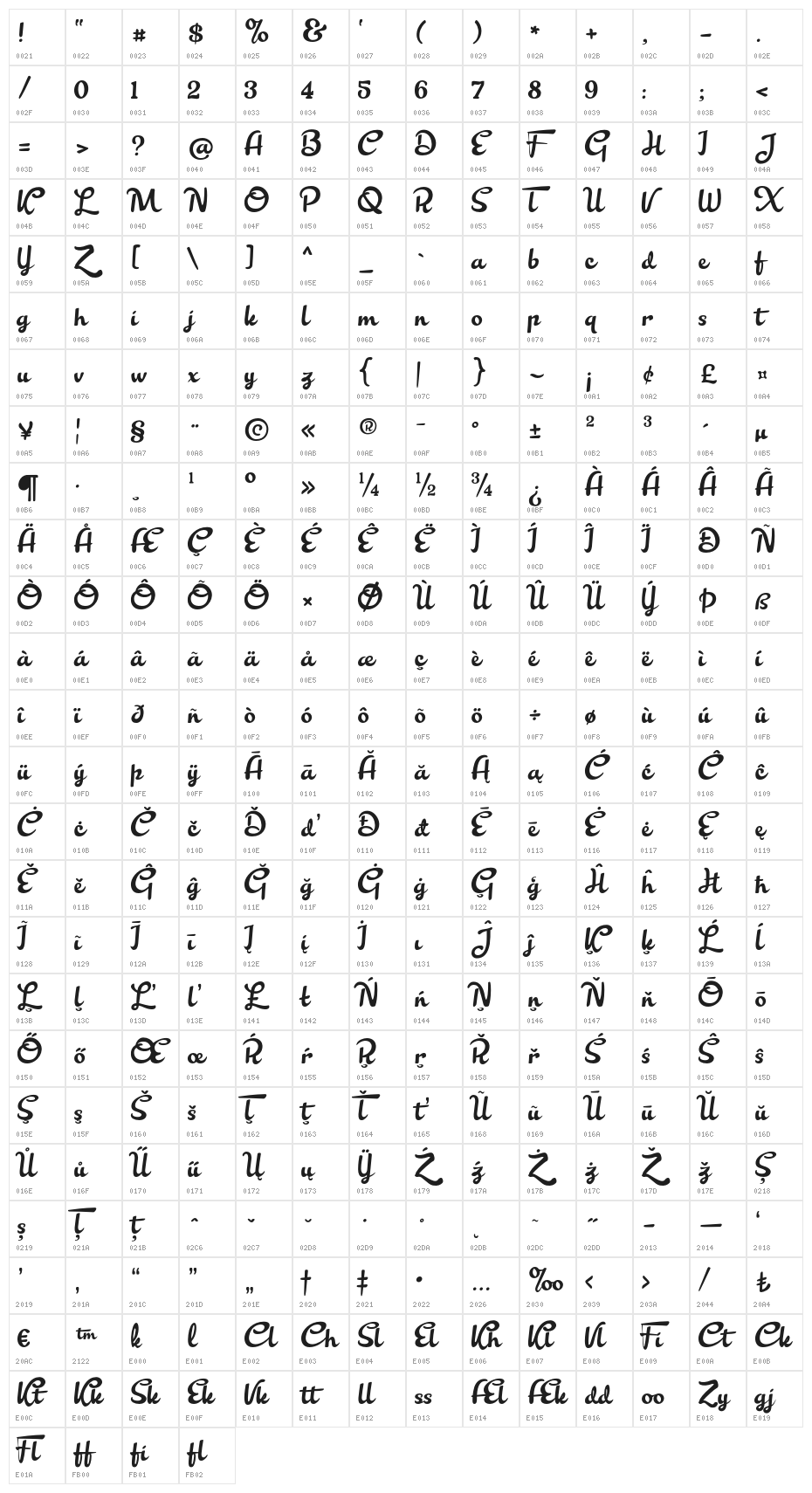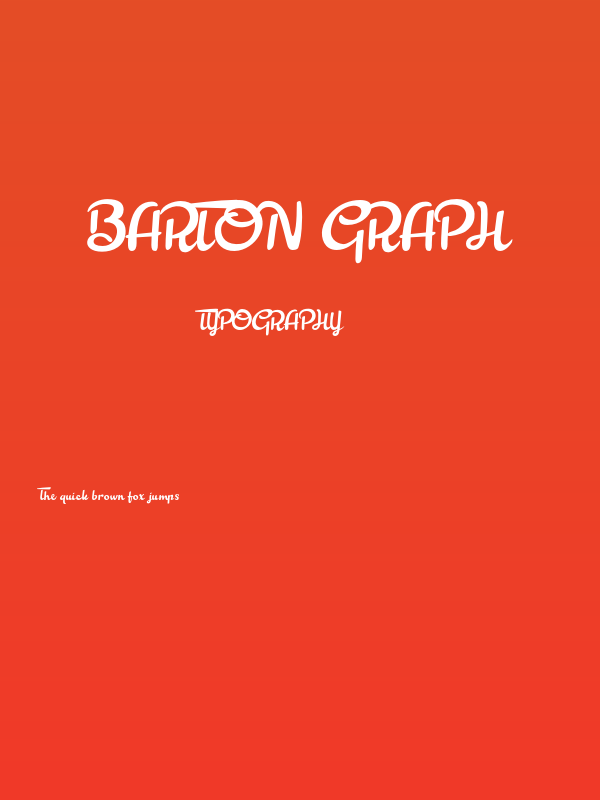
Barton Graph Font
| Anwendungsfall | Logos, Invitations, Greeting Cards |
| Vorgeschlagene Projekte | Ideal for creative projects such as invitations, greeting cards, logos, and branding materials that require a touch of elegance and playfulness. |